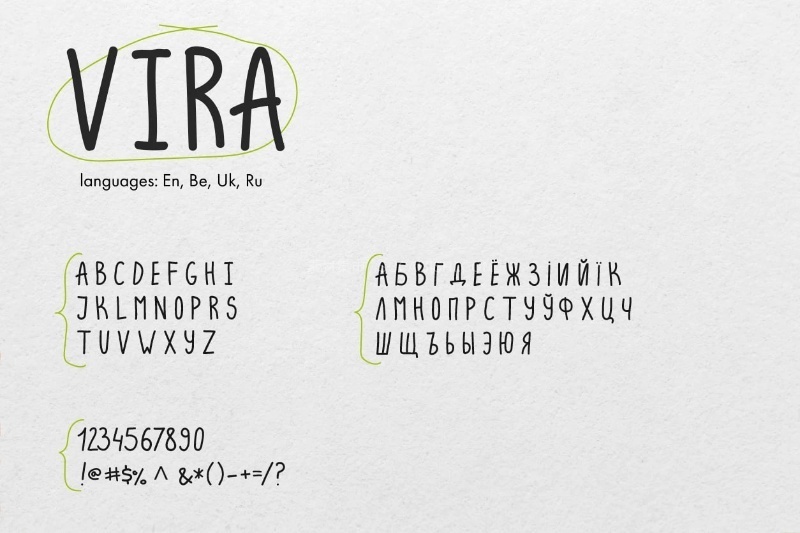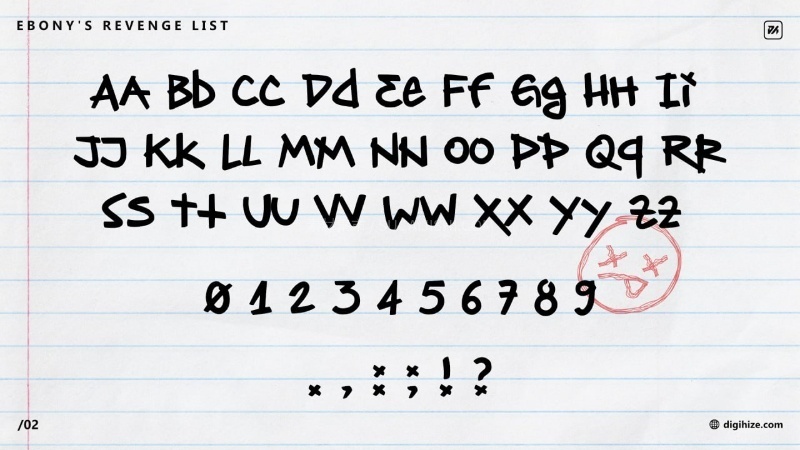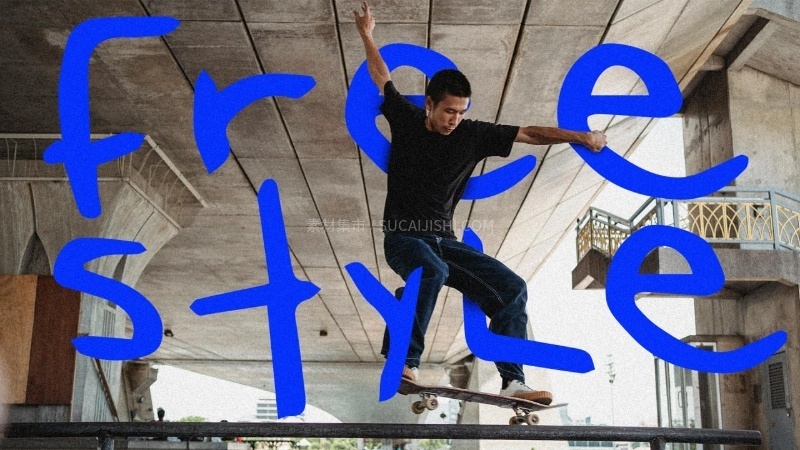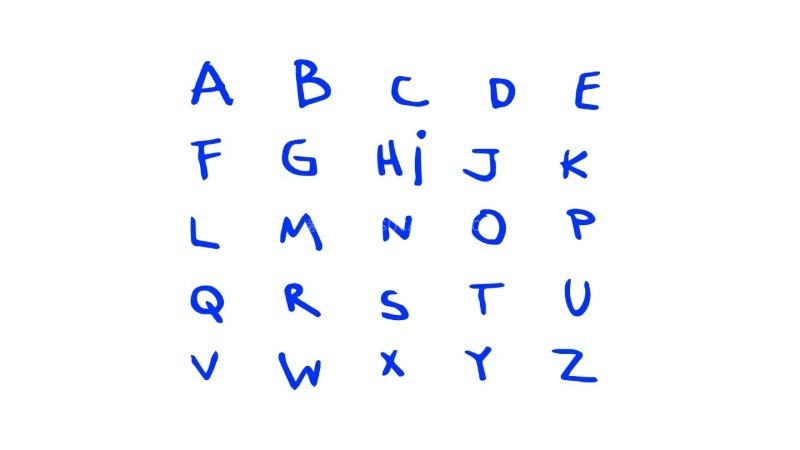
6款自带松弛感的英文字体合集
这套合集精选了6款自带自然、随性、温暖氛围的英文字体,笔触多为圆润或不规则的手写风格。它们能够瞬间为您的设计带来轻松、无压力的“松弛感”,非常适合打造亲切、人性化、慢节奏的生活美学和品牌形象。
Vira
一款充满自然松弛感的手写风格字体。其笔触圆润,线条流畅,展现出温暖而随性的个性。非常适合用于咖啡馆、休闲品牌、创意海报或任何需要亲切手绘感的项目。
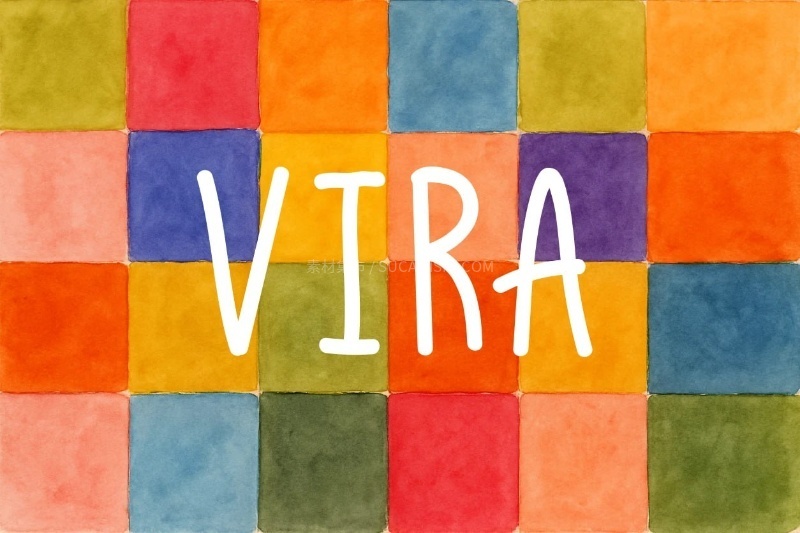
Ebony's_Revenge_List
一款充满力量感和街头风格的马克笔涂鸦字体,完美模拟了粗犷、随意的马克笔手写效果。笔触大胆且富有张力,非常适合表达叛逆、个性的主题,为您的设计增添强烈的视觉冲击力。
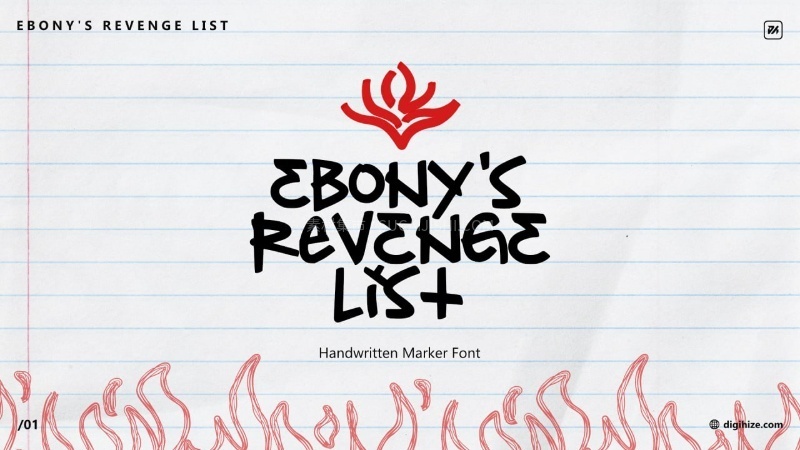
Left Hand
一款具有独特风格的书写字体,特有的随性和倾斜笔触,打破了常规,为设计带来一种不拘一格、个性鲜明的艺术感。非常适合需要展现独特创意和自由精神的项目。
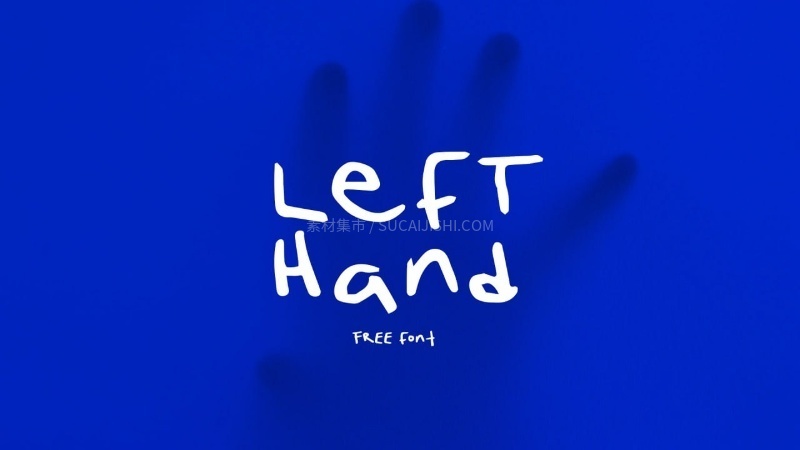
Lumeyra
一款充满个性的纯手写字体。其最大的特点在于不规则、富有生命力的线条,完美还原了快速手写时的自然与随意感。这款字体为设计带来了真实、随性、充满人情味的独特触感。
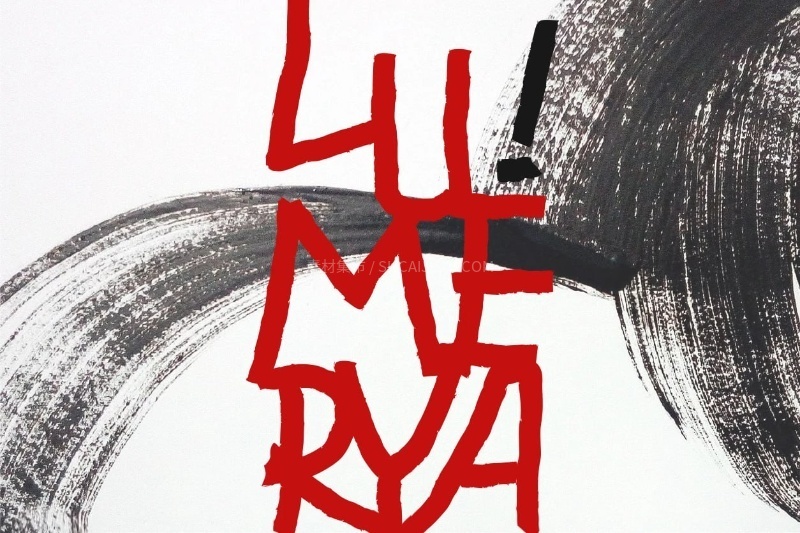
Madness Rogue
一款兼具美观、优雅与时尚感的现代显示手写字体。其休闲的笔触风格,能在设计中同时展现出阳刚与阴柔的独特气质。非常适合用于打造高端、个性化的品牌形象和内容。
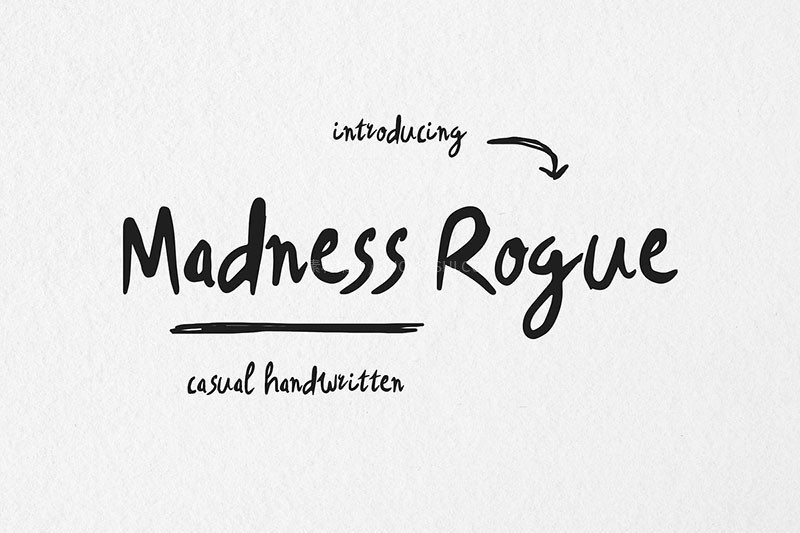
Omiren
一款富有表现力的手写字体,旨在为您的创意项目增添自然、人性化的质感。Omire 以其不规则的笔触和俏皮的流畅性,捕捉到了真实手写体的精髓——温暖、亲切、个性十足。